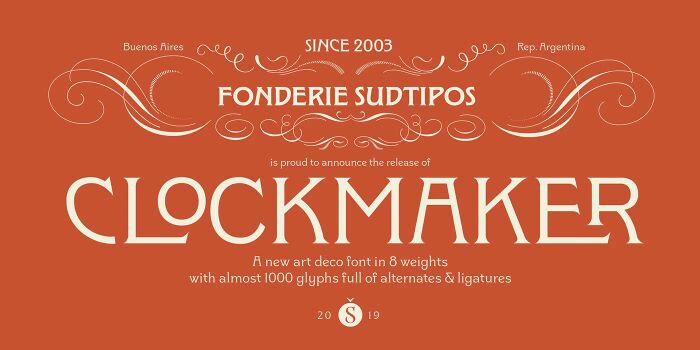
Top 10 xu hướng font chữ hot nhất trong thiết kế đồ họa năm 2022
Kiểu chữ là một yếu tố quan trọng như vậy trong thiết kế và truyền thông nói chung. Bởi vì không chỉ là thông điệp thực tế mới có vai trò quan trọng trong việc truyền tải một thông điệp nào đó, mà còn phải suy nghĩ về loại phong cách mà thông điệp đó được thực hiện. Trong cùng một văn bản thuần túy có thể đưa ra một thông điệp hoàn toàn khác khi nó được đặt bằng phông chữ khác nhau. Vì vậy bạn cần lưu ý để chọn kiểu phông chữ một cách khôn ngoan và xác định đâu là kiểu chữ phù hợp nhất cho thương hiệu hoặc thiết kế của bạn. Bài viết là một số font chữ hot nhất trong thiết kế đồ họa 2022. Hãy cùng Top Share tìm hiểu nhé!
1
Neue Nouveau
Phong cách này mang lại cho thiết kế của bạn một cảm giác hoài cổ hiện đại. Thường được sử dụng kết hợp với tông màu đất tự nhiên và đồ trang trí bằng hoa. nó chỉ đưa bạn đến thời kỳ Phục hưng. Sự kết hợp giữa các đường cong tự nhiên, các góc cạnh sắc nét và các đường serifs tinh tế tạo nên sự thú vị khi nhìn vào và vẫn mang lại cảm giác độc đáo cho thiết kế của bạn.
2
High Contrast Serifs
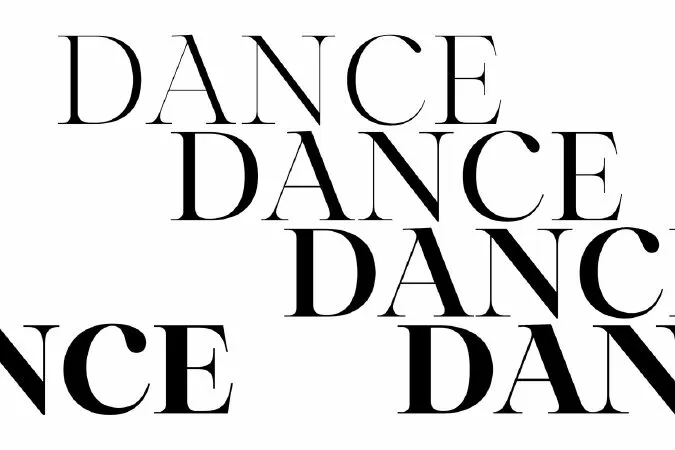
Một xu hướng typography đang trở nên phổ biến trong vài năm qua là 'High Contrast Serifs'. Sau một thời gian dài chủ nghĩa tối giản và sự bùng nổ của Sans-Serifs, nhiều nhà thiết kế bắt đầu tạo cho thiết kế của họ thêm một số đặc điểm bằng cách sử dụng các serifs có độ tương phản cao. Sự tương phản lớn về độ dày giữa các mẫu chữ này mang lại cho nó một cảm giác chắc chắn về chất lượng và trải nghiệm sản phẩm cao cấp sẽ khó hơn rất nhiều với kiểu chữ sans serif hiện đại.
Độ tương phản càng lớn, nó trông càng thú vị và các nhà thiết kế kiểu mẫu trên khắp thế giới chắc chắn đang đẩy mạnh ranh giới của những gì có thể để tạo ra những diện mạo hoàn toàn mới.
3
Phông chữ Script / Viết tay
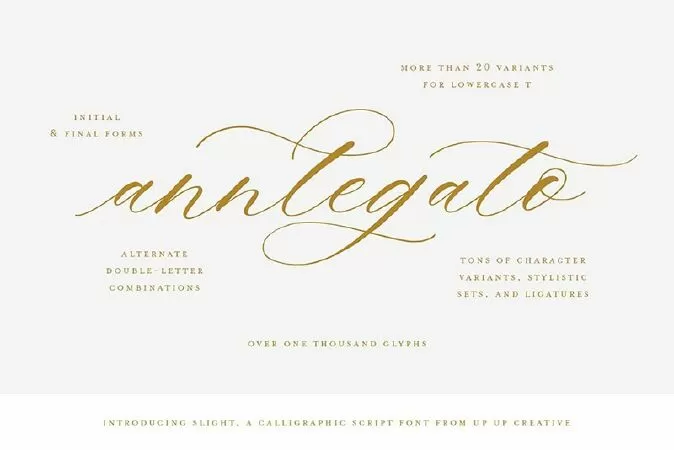
Script là một kiểu phông chữ ngày càng phát triển và có rất nhiều khả năng để sử dụng. Cho dù bạn muốn tạo cho nó một vai trò nổi bật trong thiết kế của mình bằng cách áp dụng nó vào tên sản phẩm, tiêu đề chiến dịch hoặc nhãn hiệu, bạn cũng có thể sử dụng Script cho những vị trí nhỏ hơn mang lại cho thiết kế của bạn một cái nhìn tương tự.
4
Flux
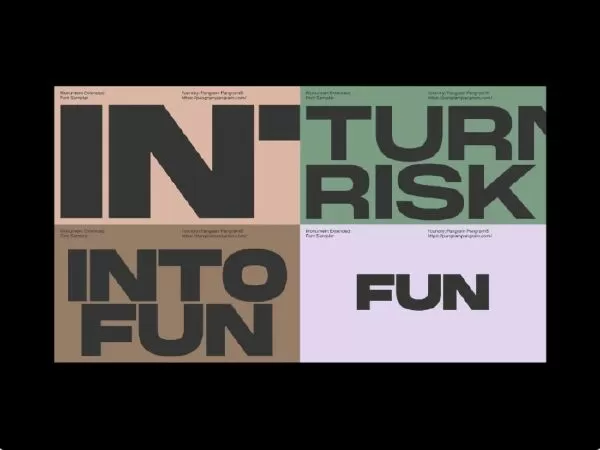
Một phong cách được xây dựng để tồn tại lâu dài và cung cấp các công cụ phù hợp để hoạt động trên công việc kỹ thuật số. Giờ đây, thế giới đang thay đổi nhanh chóng về mặt công nghệ và tất cả các khả năng mới đi kèm với điều đó. Cần có một kiểu chữ có thể thích ứng dễ dàng và mang lại hình dung thích hợp cho thời điểm này.
Phông chữ có thể thay đổi là một thành phần lớn trong phong cách này cũng như bây giờ có thể thay đổi độ rộng và độ rộng phông chữ theo cách thủ công. Bạn không còn phải chọn giữa các kiểu phông chữ được tạo sẵn trong một kiểu chữ mà là sử dụng đầy đủ không gian bạn có và lấp đầy toàn bộ màn hình.
Các chữ cái mở rộng, các hình thức được cắt xén và các đường cơ sở uốn cong, kiểu chữ này mang lại sự rung cảm phù hợp cần thiết để bắt đầu giai đoạn mới này.
Modern Organic
Typography ngày càng trở nên biểu cảm hơn để nổi bật hơn so với phần còn lại hoặc để tạo ra một sự rung cảm nhất định cho thương hiệu, thiết kế của bạn. Và trong trường hợp bạn muốn đạt được điều đó mà không sử dụng phông chữ hữu cơ được làm quá kỹ hoặc kiểu viết tay làm mất đi một logic nhất định đằng sau kiểu chữ của bạn, thì kiểu Modern Organic này có thể là kiểu dành cho bạn.
Tính dễ đọc là một yếu tố quan trọng đối với kiểu chữ nhưng trong một số trường hợp nhất định, bạn có thể hy sinh điều này một chút để tạo tiêu đề thu hút sự chú ý của người xem và cho phép người đọc khám phá những gì nó nói trên đó. Mặc dù không được khuyến nghị cho biển báo giao thông, nhưng nó hoạt động hoàn hảo cho các thương hiệu hoặc sự kiện hiện đại, sáng tạo với khán giả nhỏ tuổi.